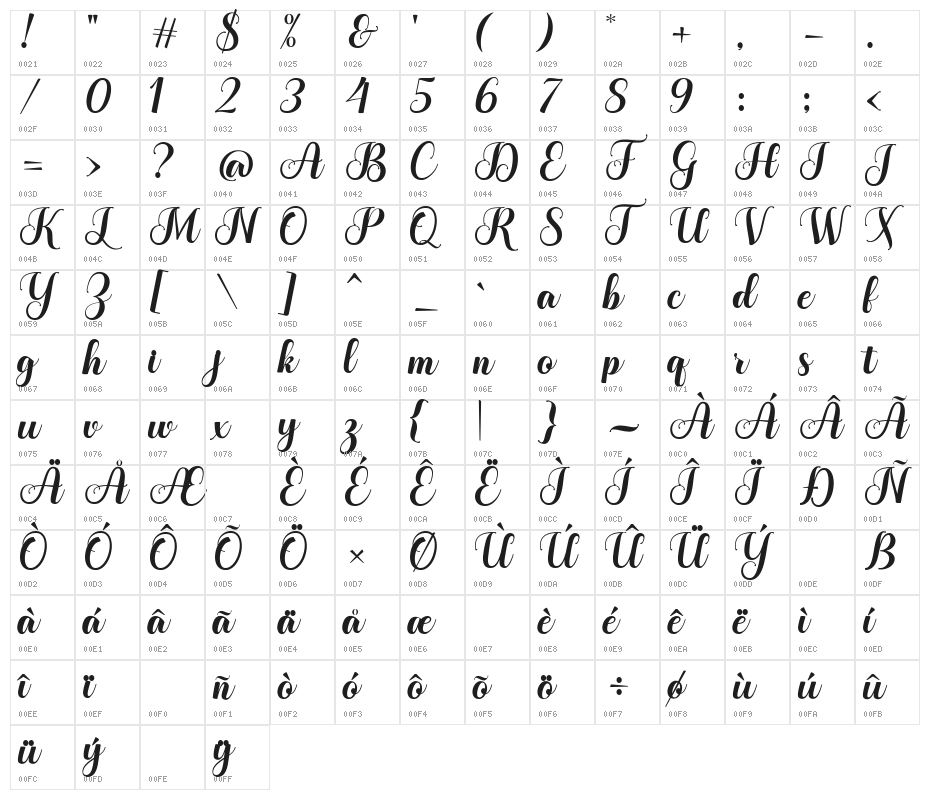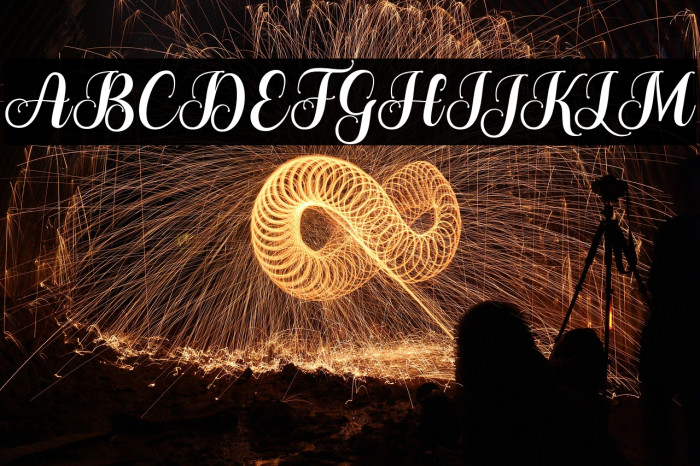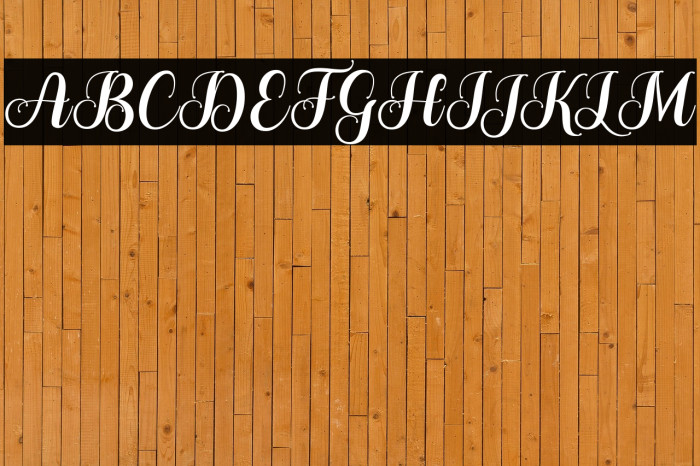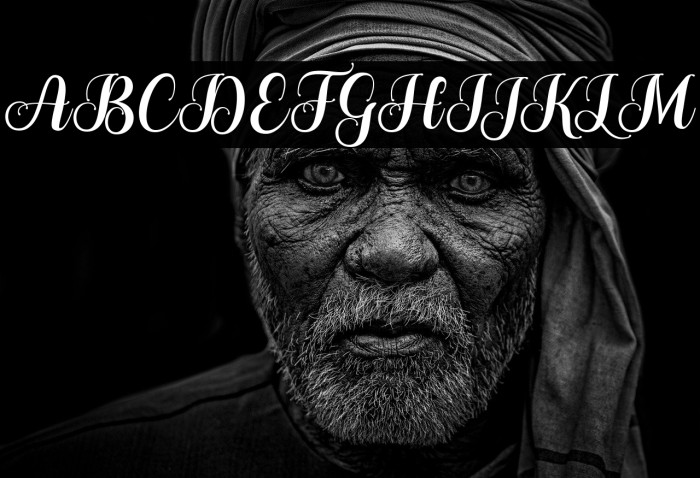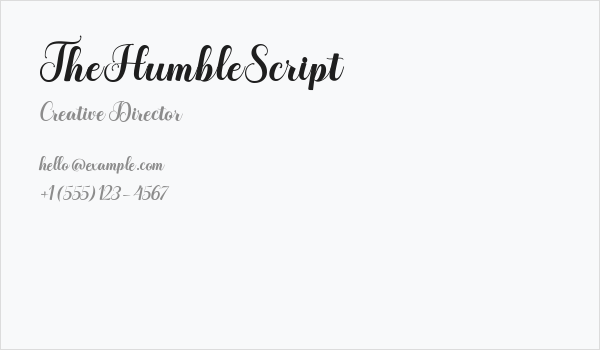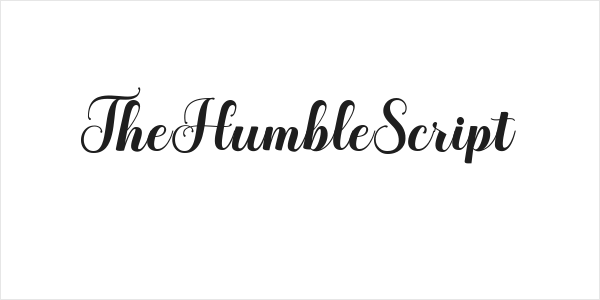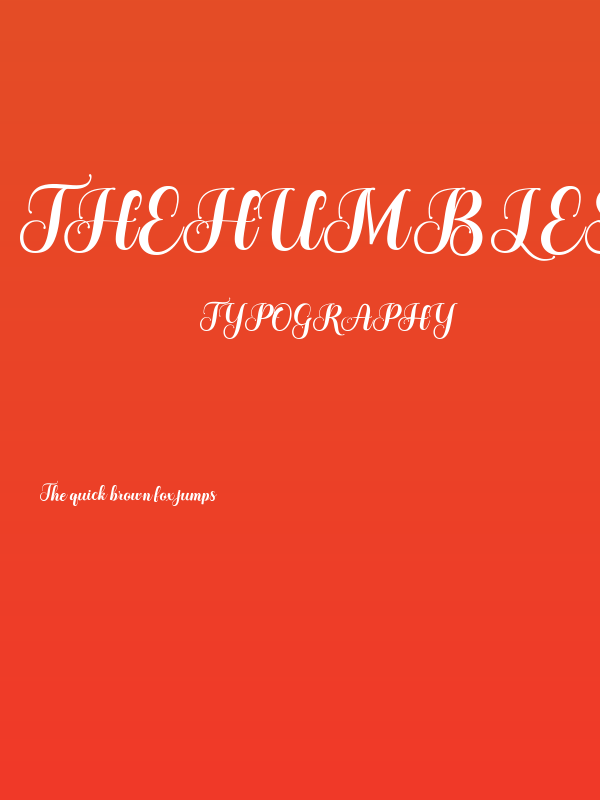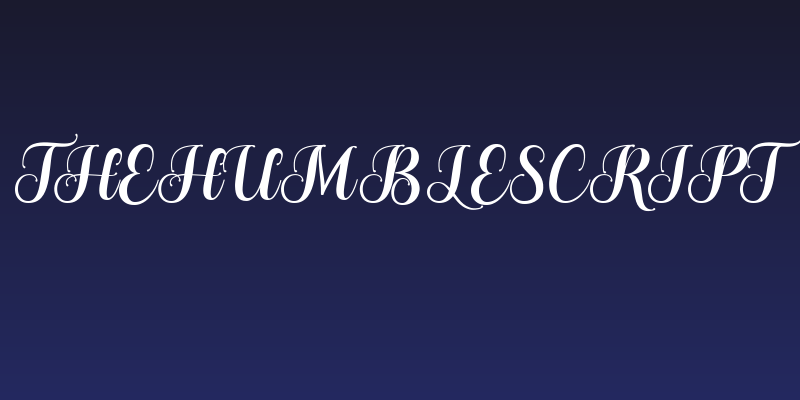
TheHumbleScript Font
| Stile generale | Elegant |
| Caso d'uso | Logos, Invitations, Branding |
| Progetti proposti | Ideal for wedding invitations, luxury branding, elegant packaging, and high-end product labels. |